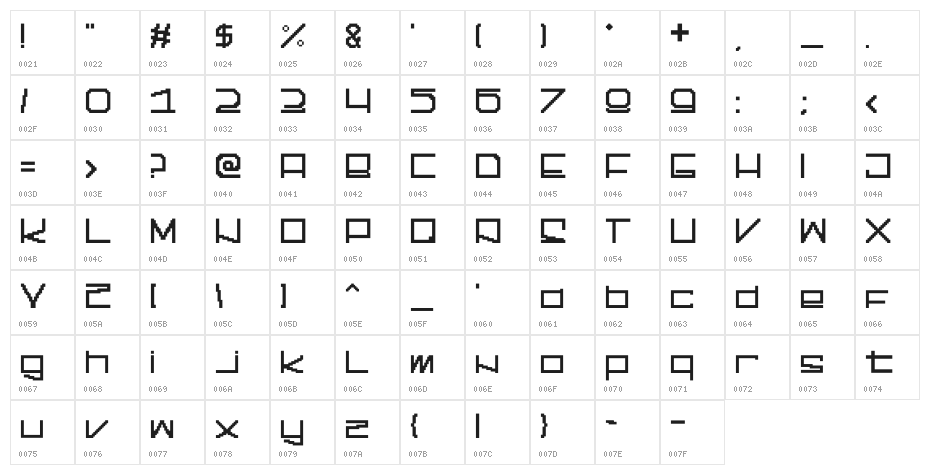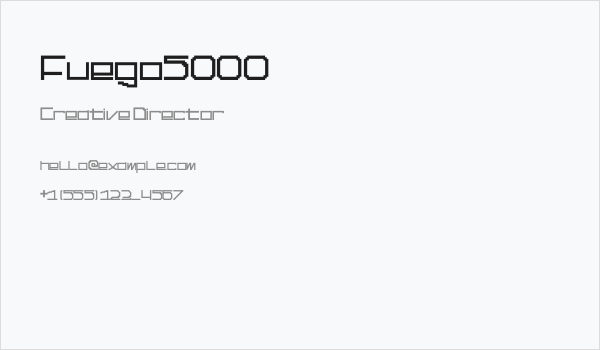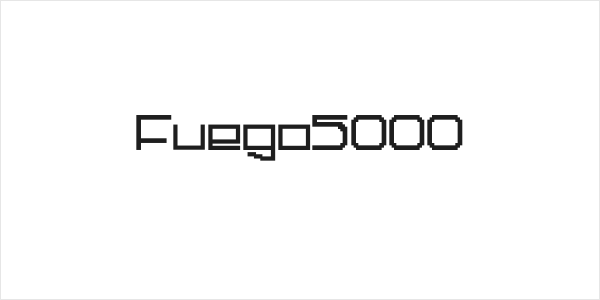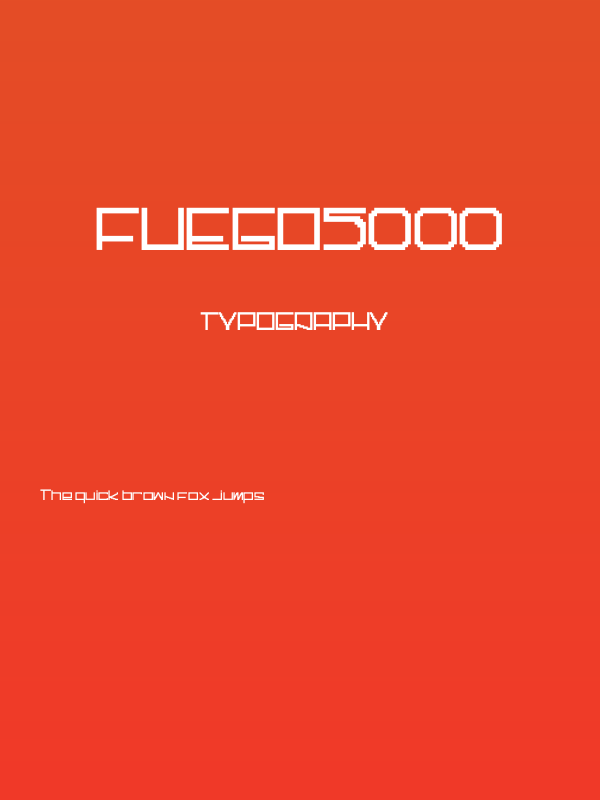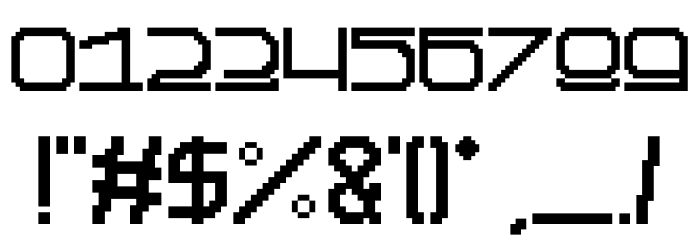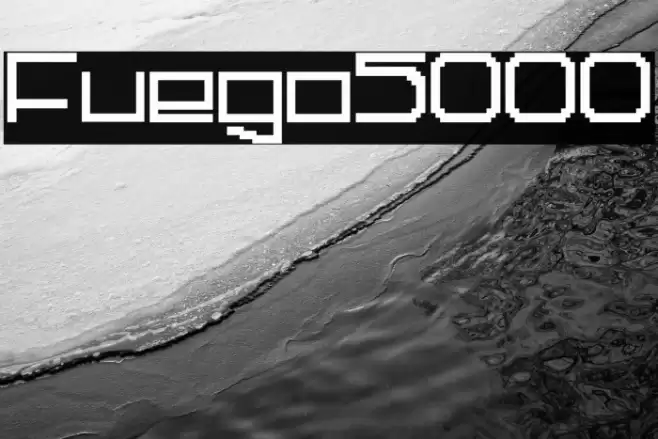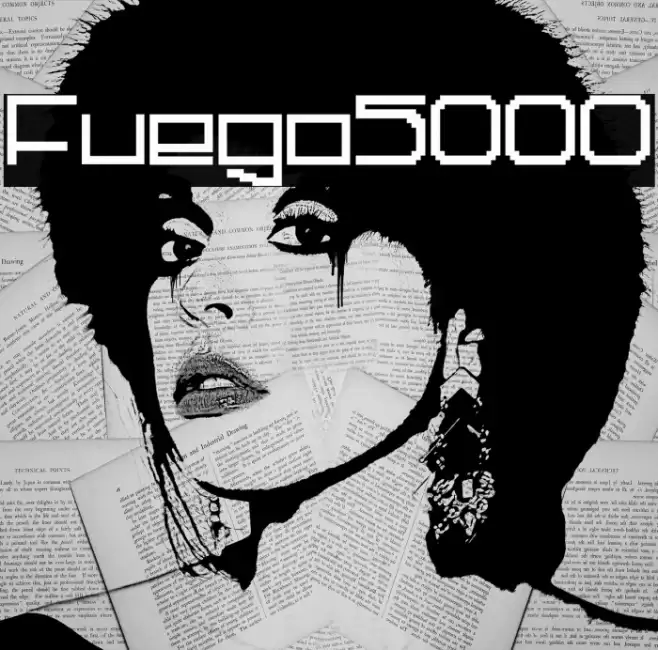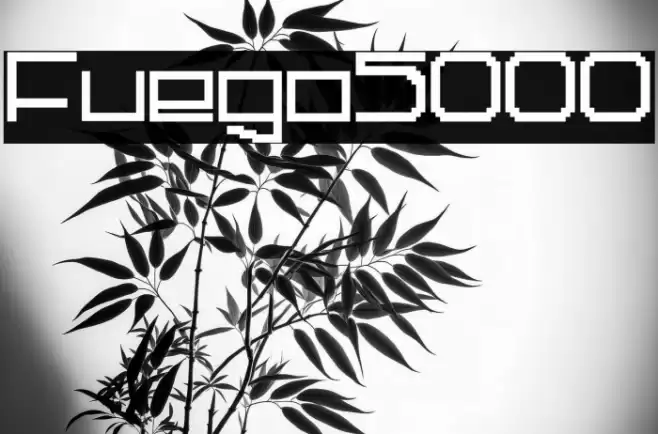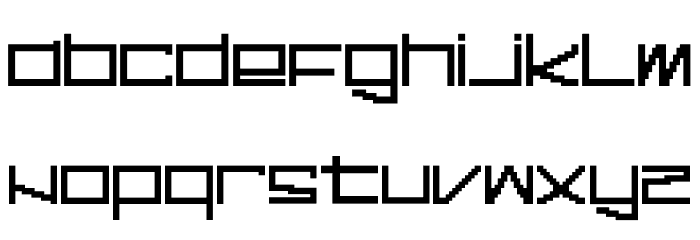
Fuego5000 Font
| Categorie | Pixel |
| Stile generale | Retro, Digital |
| Caso d'uso | Logos, Posters, Digital Art |
| Progetti proposti | Ideal for video game designs, retro-themed posters, digital art projects, and tech-related branding. |